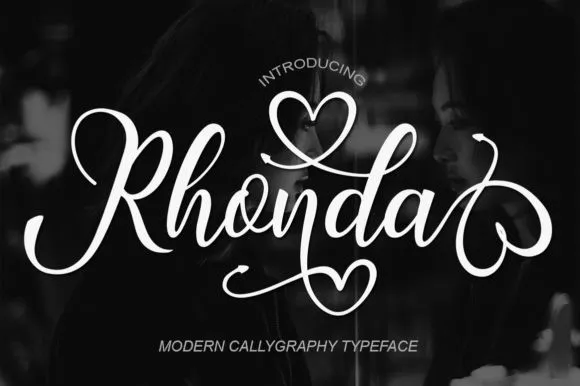
Rhonda Calligraphy Font – Download Grátis
Introduzimos a fonte Rhonda Calligraphy Font, que traz uma chamada fresca e elegante. Especialmente adequada para vários usos conforme suas necessidades, esta fonte é perfeitamente indicada para apaixonados por ela. Ela oferece um toque leve e sofisticado, tornando-a um must-have para designers de arte. Get inspired por sua magia romântica! É especialmente apropriada para mídia de casamento, capas de livros, cartões de boas-vindas, logotipos, marcas, cartões de visita e certificados, ou seja, qualquer tipo de projeto gráfico que exige um clássico, formal ou luxuoso. A Rhonda Calligraphy Font foi projetada por bbakey.